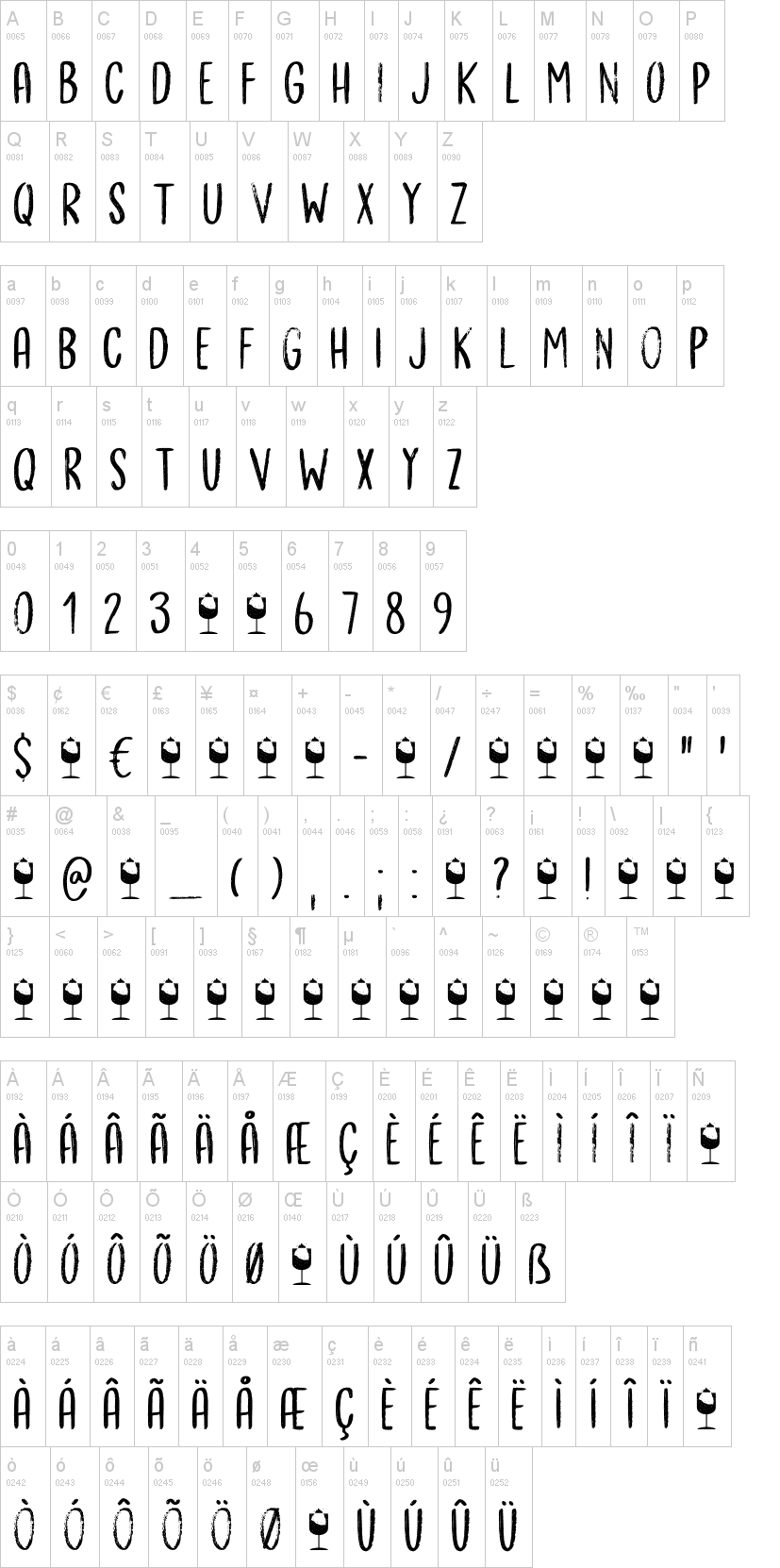
Bergie Seltzer
Bergie Seltzer 是一款由 Fontfabric 出品的欧美风格粗体字体,它以它独特的外观和结构,融合了传统的欧美字体设计,具有细腻的线条和温暖的色调。它的字体笔画粗细程度和高度的变化,使它的文字看起来十分温柔,而且拥有细节丰富的字形,能够表达出不同的情感。它的字体外观简洁大方,适合用于各种类型的设计,如报纸、海报、广告和书籍等。
Bergie Seltzer是一款非常不错的手写艺术字体,具有很好的视觉感,适合于文化类的宣传设计、商业类品牌的广告和产品包装设计以及个性化文字排版等较多场景。